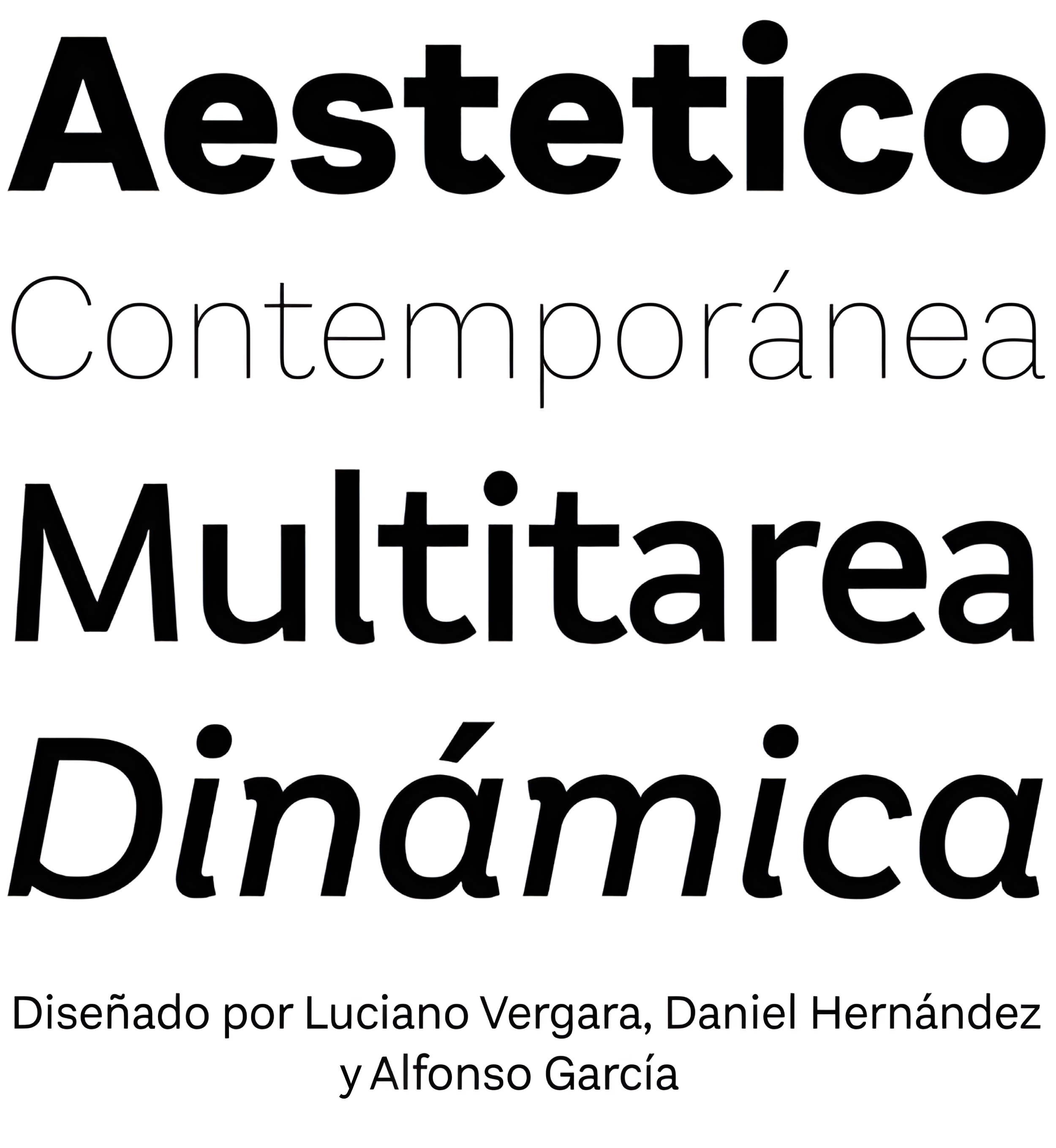
| Año | 2020 |
| Créditos | Luciano Vergara, Daniel Hernández, Alfonso García |
| Descripción | Esta hermosa fuente explora 3 estilos muy individuales de un mismo tipo de letra. Cada estilo rinde homenaje a los tipos de letra sin gracias clásicos al tiempo que añade un toque contemporáneo a sus características. Con estilos formales e informales, Aestetico explora cómo las formas y curvas de las letras cambian su percepción y enfoque. Las letras informales son más redondeadas y extravagantes, mientras que el estilo formal utiliza formas de letra sin gracias más tradicionales. El juego completo (54 estilos) consta de 3 familias hermanas, cada una en 9 pesos con cursivas a juego. |
| Familia(s) | Aestetico |
| Estilos | 54 |